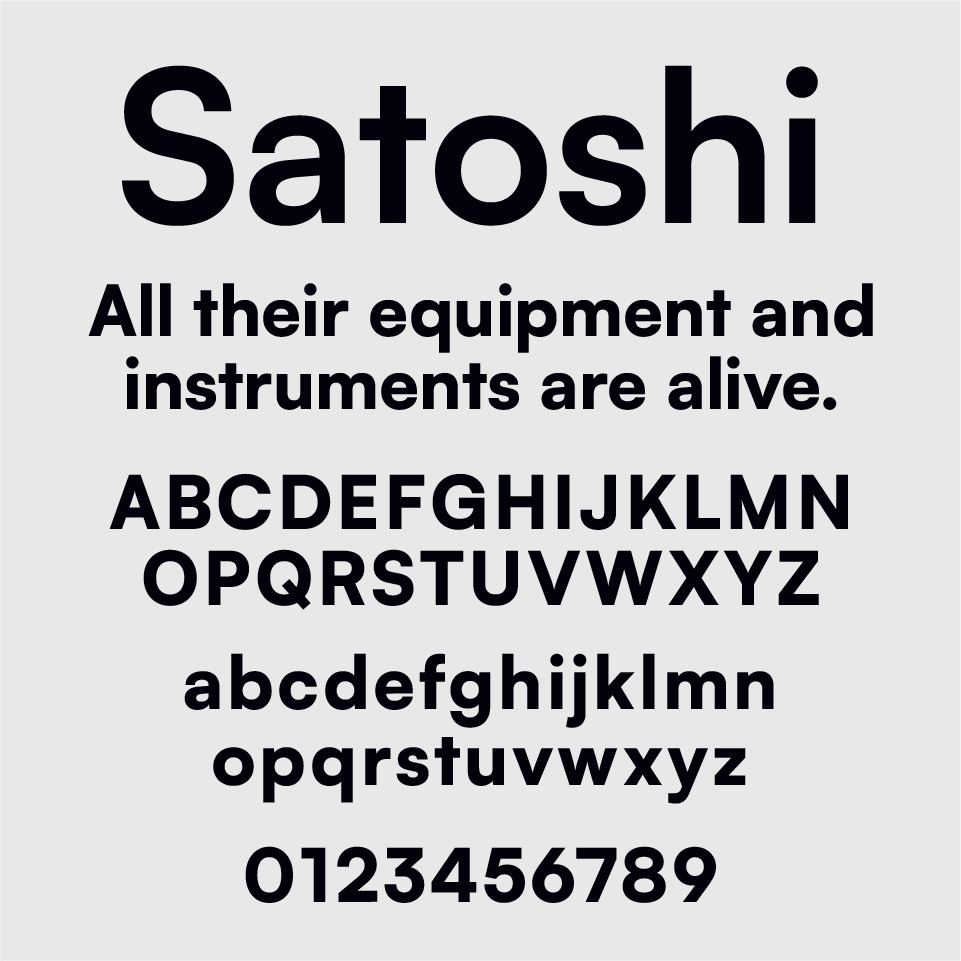
Satoshiフォントは、すっきりとしたジオメトリックなサンセリフで、現代的でミニマルな印象を持つフォントです。
丸みを帯びたシンプルな造形は清潔感があり、余白を大切にした設計と相性が良いフォントです。
モダンでクセがなく、それでいて親しみやすい雰囲気があるため、テック企業のUIやスタートアップのロゴ、Webサイトの本文まで幅広く活用できます。どこか中立的でフラットな佇まいが、ブランドや情報を引き立てる黒子のような存在。
近年では、日本のWebデザインでも多く取り入れているのを見かけるフォントです。